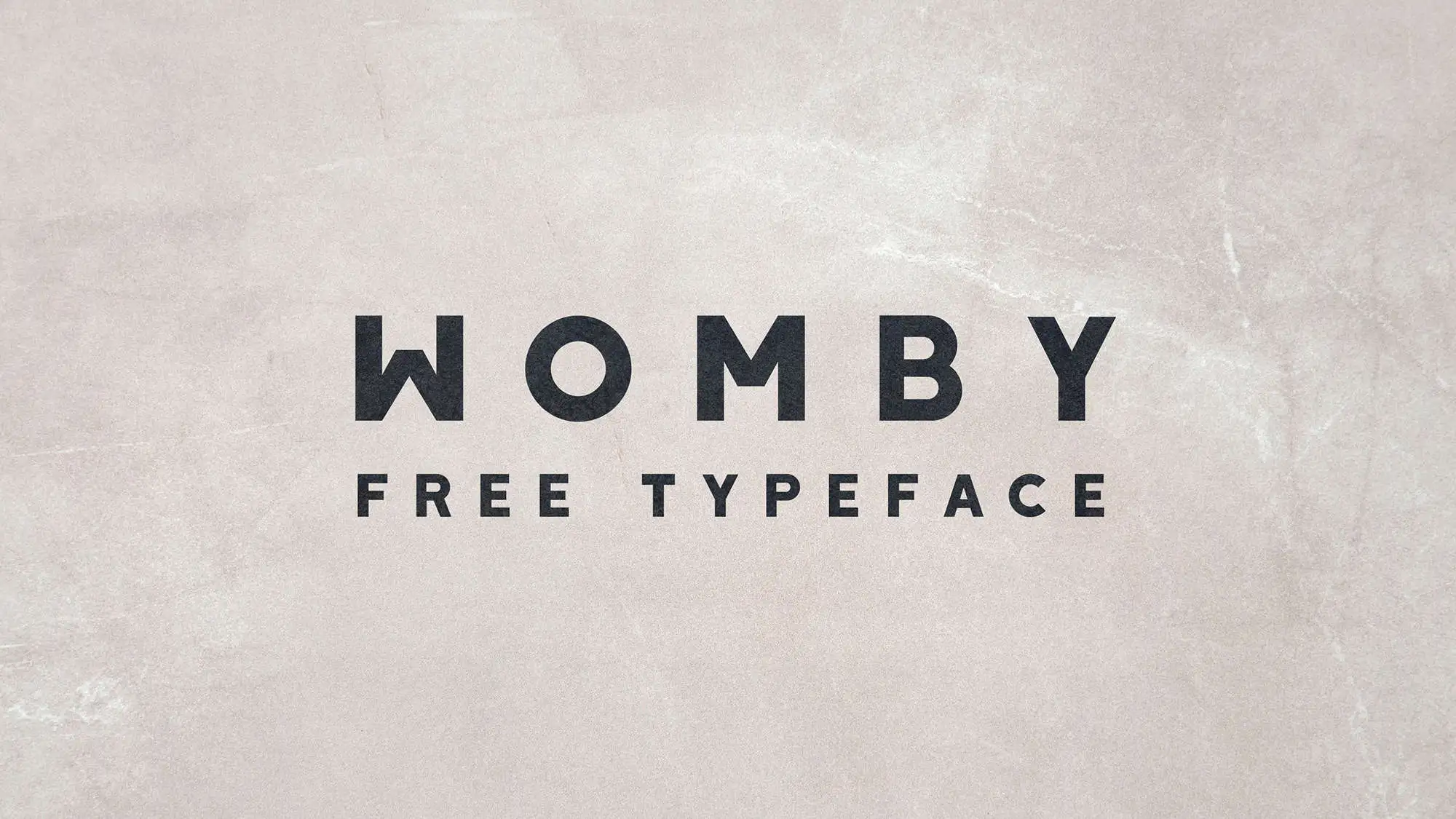
A Womby Font é uma elegante seleção do mundo dos tipos de letra sans serif que se destaca pela sua simplicidade e modernidade. Seus traços leves e retos dão um toque clean a qualquer projeto visual, seja ele impresso ou digital. A designer cagrikara criou uma fonte pronta para destacar texto em situações como o layout de emails profissionais ou anúncios online, oferecendo um acabamento minimalista que destaca sem perder a utilidade funcional. A Womby é perfeita tanto para textos simples quanto para design gráfico mais elaborado, garantindo uma experiência visual harmônica e contemporânea em qualquer plataforma digital ou impressa.